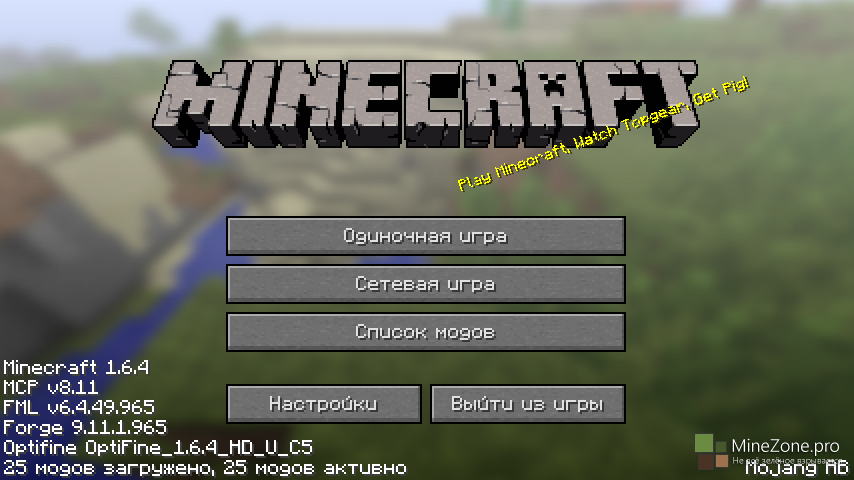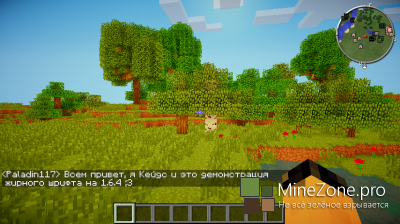
[1.6.4] Жирный Русский Шрифт!
Не понимаю?
Зачем так мудрить, не проще ли просто файл с шрифтом, запихать в архив с ресурпаком, а не мудрить, и создавать новый профиль? =/
P.S. Но за шрифт всё равно +
Vtaroi!1!1!1!!! "Жирный" текст мне очень нравится. Не люблю всякие "Бонусы", а так новость хорошо оформлена и полезна. :3. Плюс, крч.
слово "жирный русский", сразу ассоциация с русской бабой >_>
Мне из английским языком нормально...А за старания плюс!
Неплохо,я лично считаю что эта сборка поможет в игре!